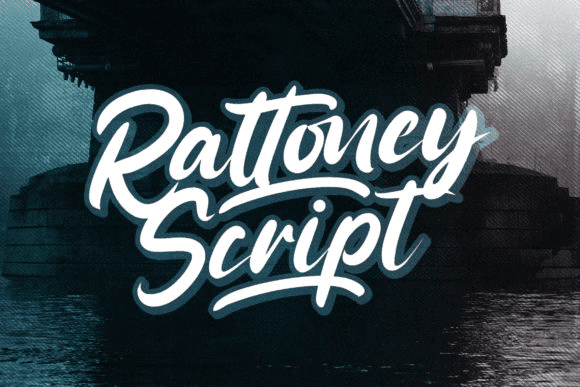
Название: Rattoney Font
Rattoney - это великолепный, скорописный и смелый рукописный шрифт, созданный, чтобы придать стильный штрих вашим заголовкам и логотипам проектов.
Этот шрифт читается как сильный, уверенный и динамичный и может придать тонны ностальгического характера вашим дизайнерским работам.
Название: Rattoney Font
Rattoney - это великолепный, скорописный и смелый рукописный шрифт, созданный, чтобы придать стильный штрих вашим заголовкам и логотипам проектов.
Этот шрифт читается как сильный, уверенный и динамичный и может придать тонны ностальгического характера вашим дизайнерским работам.